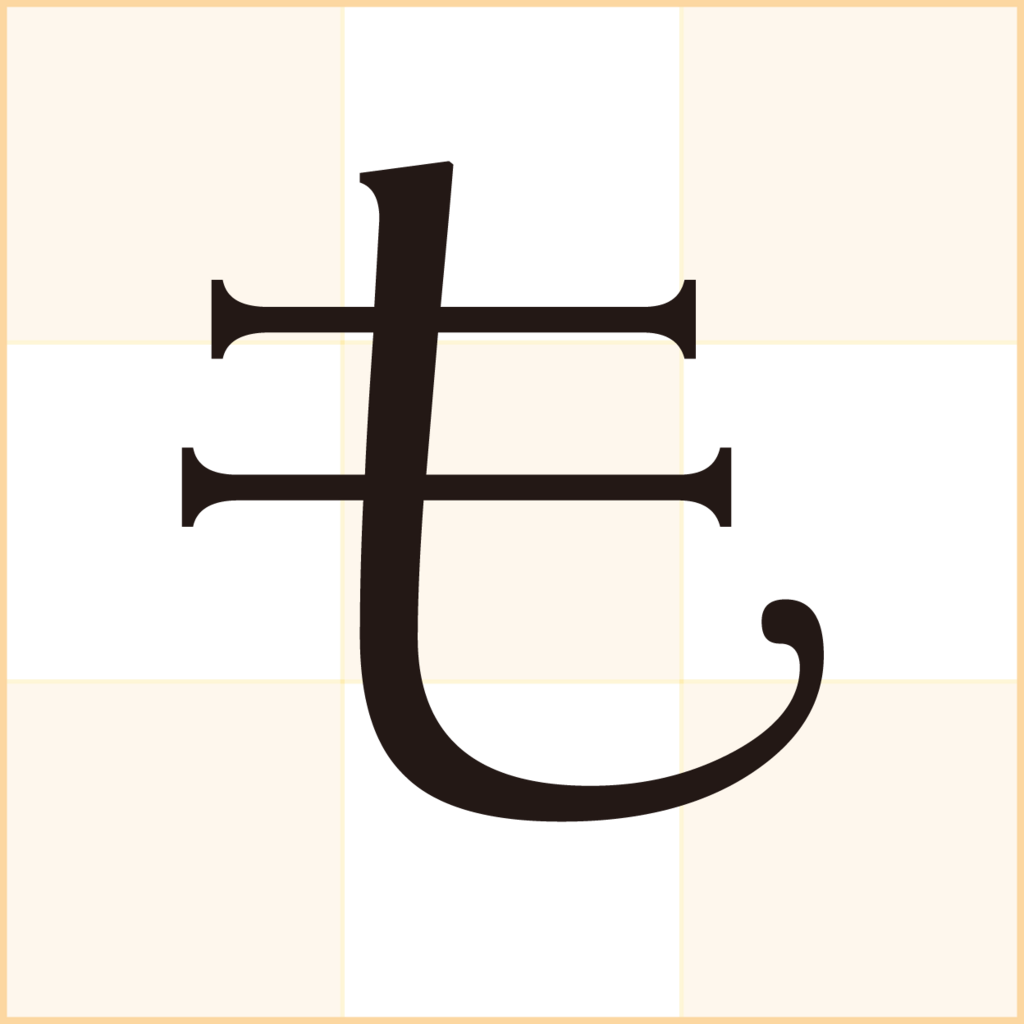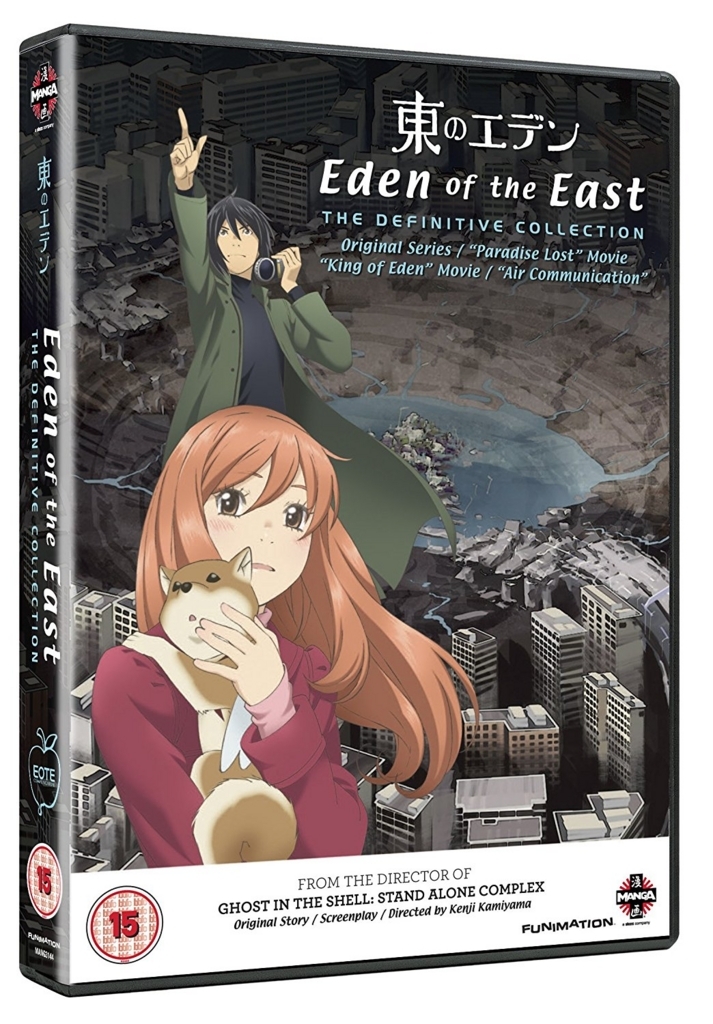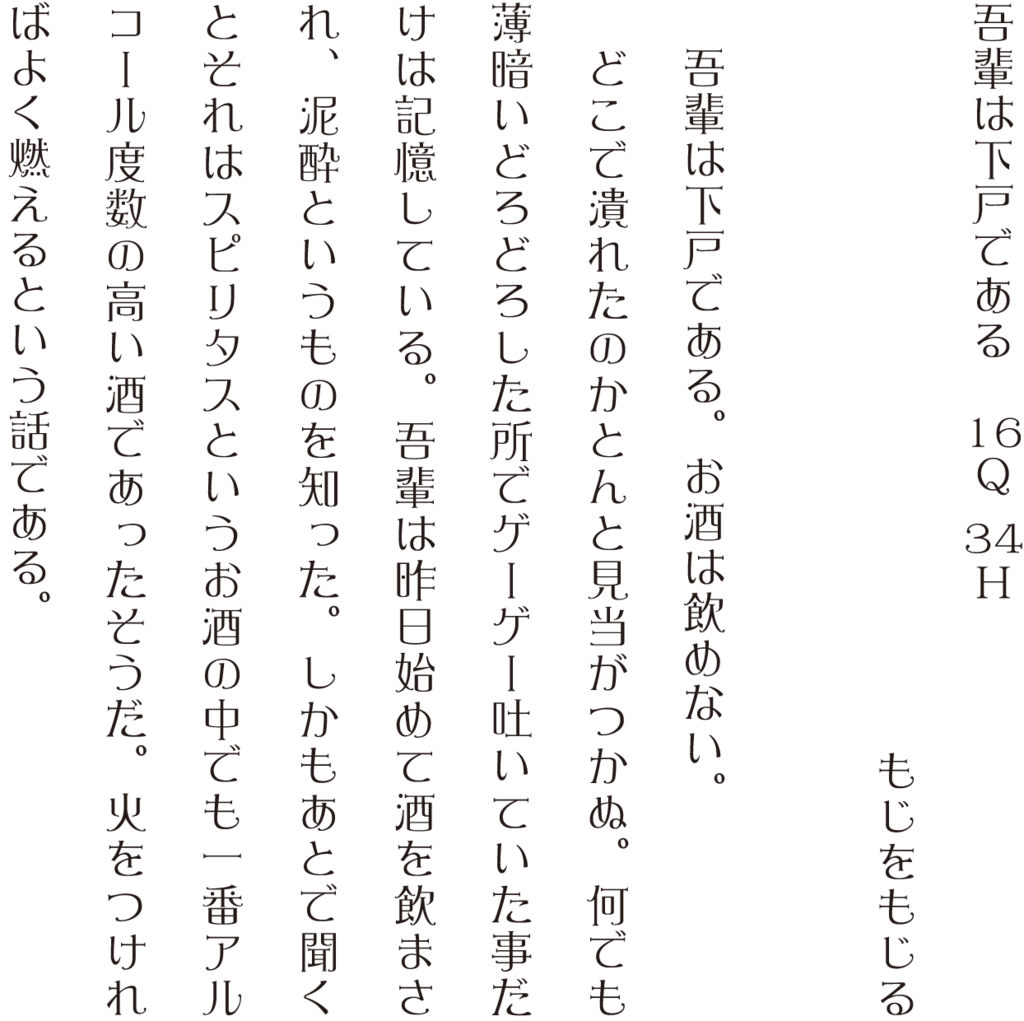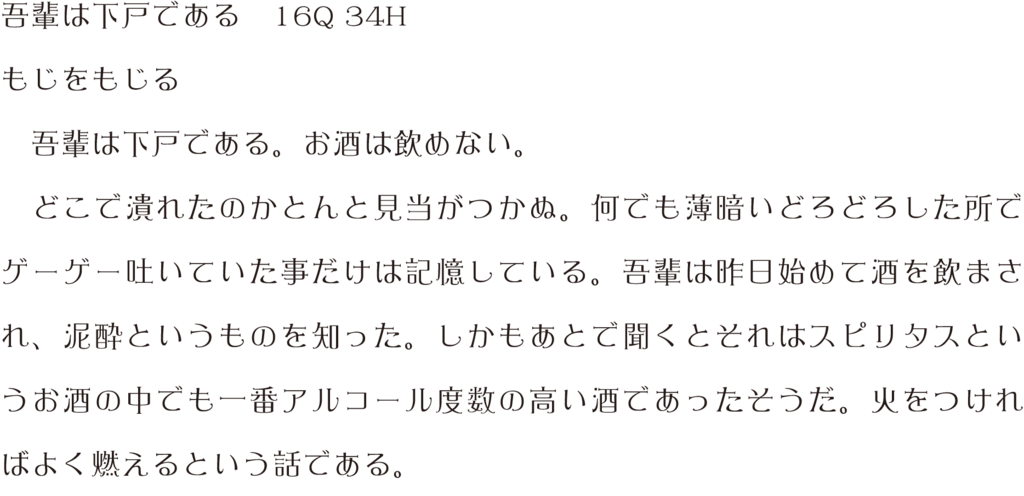
優雅宋
ストロークの先端と末端に欧文書体の花文字のような装飾が施されているのが特徴のフォントでダイナコムウェアが開発したダイナフォント(DynaFont)シリーズの1つ。
ダイナフォントの中ではロマン風書体というシリーズにカテゴライズされており、少女漫画チックな雰囲気を宿すそのデザインは、少女漫画、乙女、ガーリーといったテイストでの使用に適している。
ハチミツとクローバーや東のエデンにも使用され、羽海野チカ御用達フォントともいえる優雅宋
優雅宋は、羽海野チカの傑作漫画である「ハチミツとクローバー」や羽海野チカがキャラクターデザインを手掛けたアニメ「東のエデン」のタイトルでも使用されており、羽海野チカの描き出す世界観にもマッチしているようだ。
「王子様のプロポーズ Eternal Kiss」にダイナフォント「優雅宋」が採用
ボルテージが開発・運営する恋愛ドラマアプリ「王子様のプロポーズ Eternal Kiss」に、ダイナフォント「優雅宋」が採用されている。
「優雅宋」の採用理由として、王子様と恋愛する王道のラブストーリーということで、ロイヤル感や上品な印象のあるフォントが良いと思い採用されたとのこと。
また、文字自体に装飾が施されていたり、細い曲線を織り込んでいるこのフォントには華やかかつ洋風らしさがあり、アプリのテーマともマッチして、より世界観を引き立たせて、デコラティブで目立ちやすい点にも着目しており、訴求力のある太めのウェイトが選べるところもこのフォントの良い点だと思ったことも採用の理由らしい。
書籍「エミリときどきマーメイド」にダイナフォント「優雅宋」が採用
文響社が2021年3月11日に発売した、リズ・ケスラー氏著作で、田中亜希子氏が日本語訳、カタノトモコ氏がイラスト、稲永 明日香氏がデザインを担当した、世界中で大人気のマーメイド・ストーリー「エミリときどきマーメイド」に、ダイナフォント「優雅宋」が採用されている。
採用理由は、かわいいだけでなくエレガントさも持ち合わせている書体なので、少し背伸びをしたい年頃の読者ターゲット(小学校中・高学年~中学生)にぴったりだと感じたためとのこと。
書籍「おなかの花園 ―きみのおなかにひそむ不思議な世界 マイクロバイオームをめぐる冒険」にダイナフォント「優雅宋」が採用
化学同人が2020年12月15日に発売した、ケイティ・ブロスナン氏が作、滝本安里氏が翻訳を担当した科学絵本「おなかの花園 きみのおなかにひそむ不思議な世界 マイクロバイオームをめぐる冒険」に、ダイナフォント「優雅宋」が採用されている。
「花園」の雰囲気を出したくていろいろ探していた際、かわいらしいイラストにぴったりだったことが採用理由とのこと。公式サイトの採用事例にて、シックな色合いの表紙の中にキラキラ感も出て満足とコメントしている。
書籍「午前零時のサンドリヨン」「ロートケプシェン、こっちにおいで」にダイナフォント「優雅宋」が採用
相沢沙呼氏著書で、装画を加藤木麻莉氏、装幀を大野リサ氏が担当した、東京創元社による書籍「午前零時のサンドリヨン」および続編「ロートケプシェン、こっちにおいで 」のタイトルに、ダイナフォント「優雅宋」が採用されている。
採用理由は、サンドリヨン=シンデレラ、ロートケプシェン=赤ずきんと西洋の童話をモチーフにしているため、「優雅宋」のメルヘンチックな書体がマッチすると思ったためとのこと。
優雅宋 組見本(W3)
新元号「令和」の優雅宋書体見本
新元号「令和」の優雅宋の書体見本。